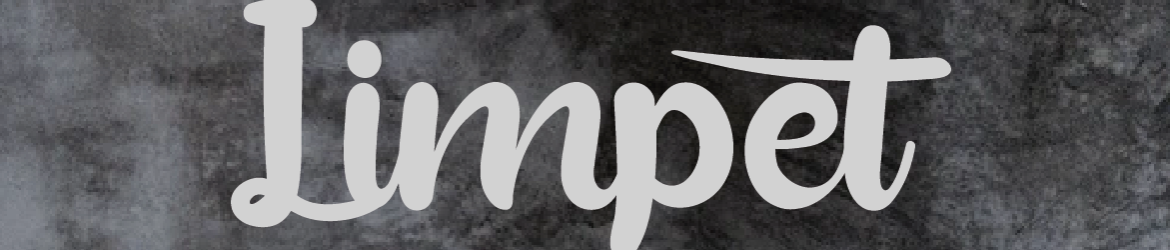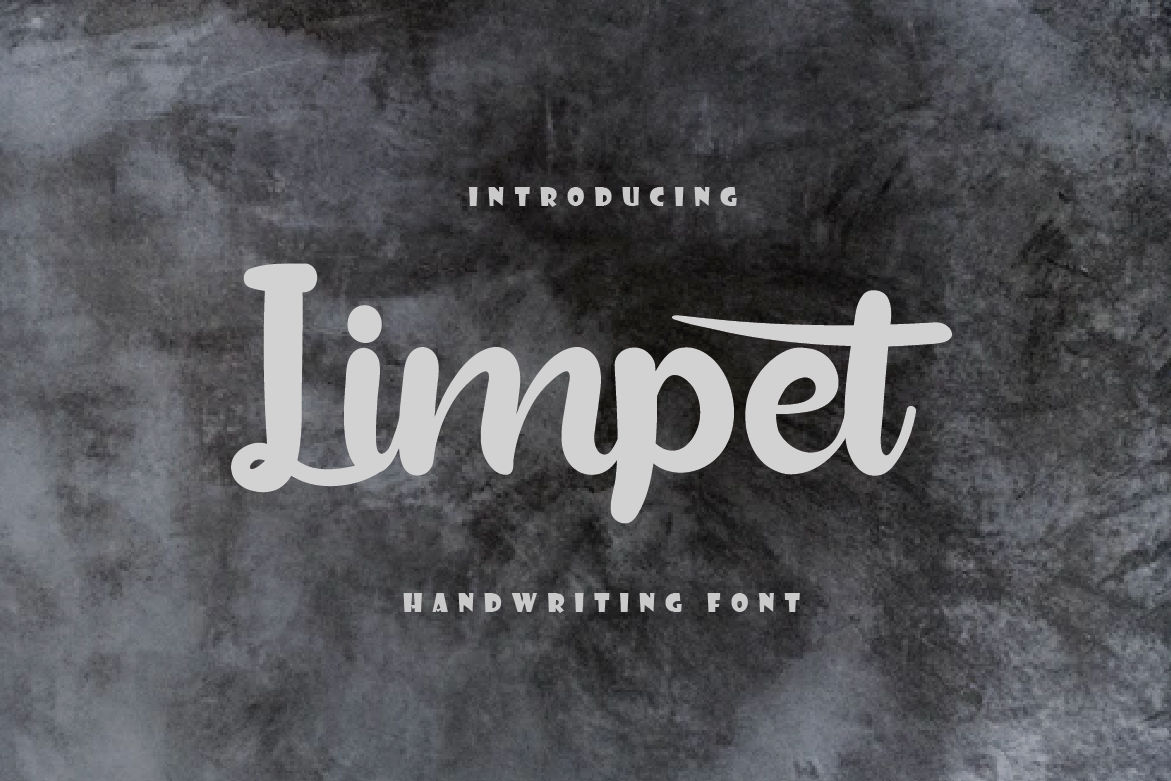
Limpet Font
A Limpet Font é uma elegante tipografia escrita à mão perfeita para transmitir mensagens com confiança, autenticidade e encanto. Especialmente adequada para ideias de crafts variadas como cartões, marcações, rótulos e muito mais. O fato de esta fonte ser PUA encoded é uma grande vantagem: você pode acessar facilmente todos os símbolos e traços. Esta escolha única de fontes escrita à mão, criada pelo Design Amour, é perfeita para qualquer projeto que busque agregar um toque único ao seu design. Seja em cartões personalizados ou rótulos elegantes, a Limpet Font proporcionará uma presença impecável, fazendo do seu trabalho ainda mais autêntico e inovador.